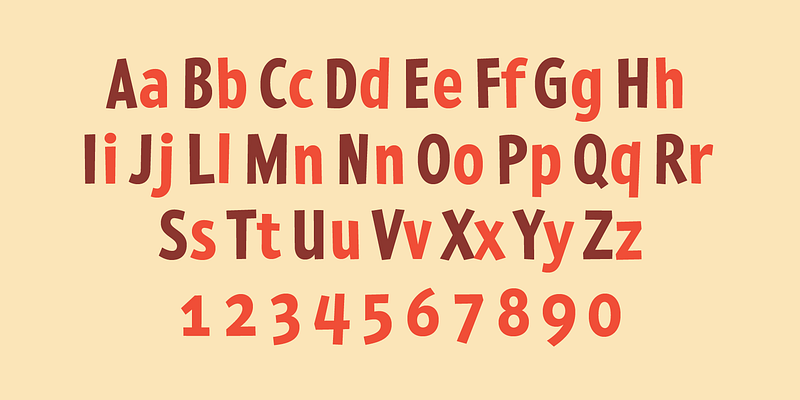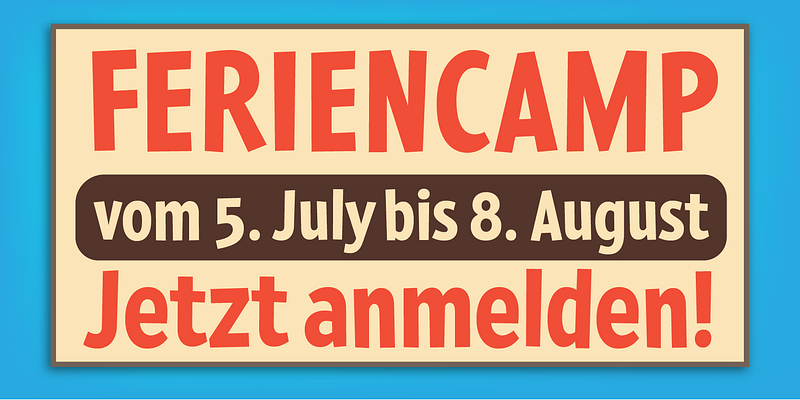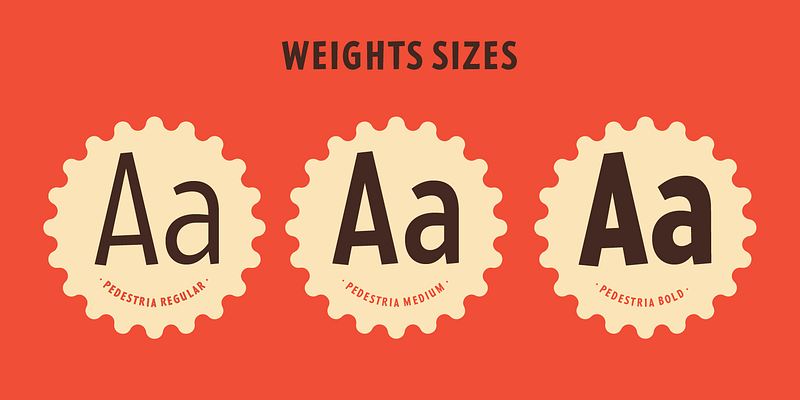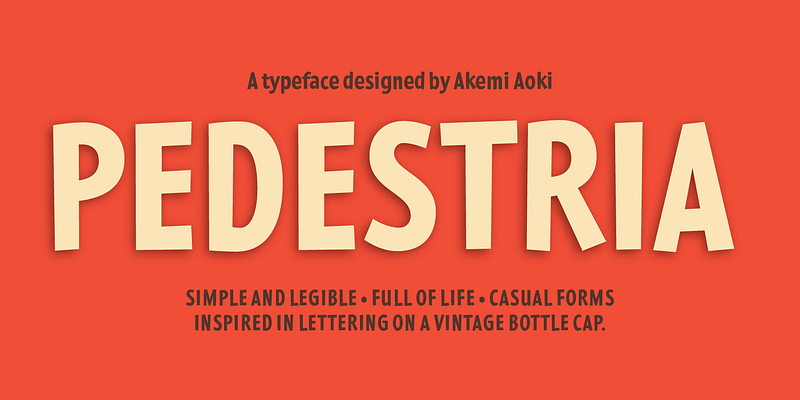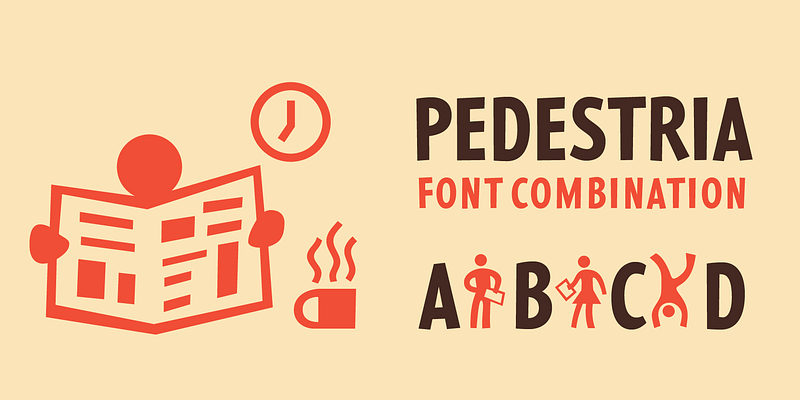
Las letras del tapón de una botella vintage fueron la inspiración para MVB Pedestria. El diseño de Akemi Aoki es sencillo y legible, pero a la vez lleno de vida, gracias a sus formas sueltas e informales. Dos conjuntos de fuentes Pict irreverentes que llevan a otro nivel los caracteres de la simbología ubicua de las puertas de aseos públicos, ofreciendo pictogramas alegres para invitaciones, publicidad e infografías.